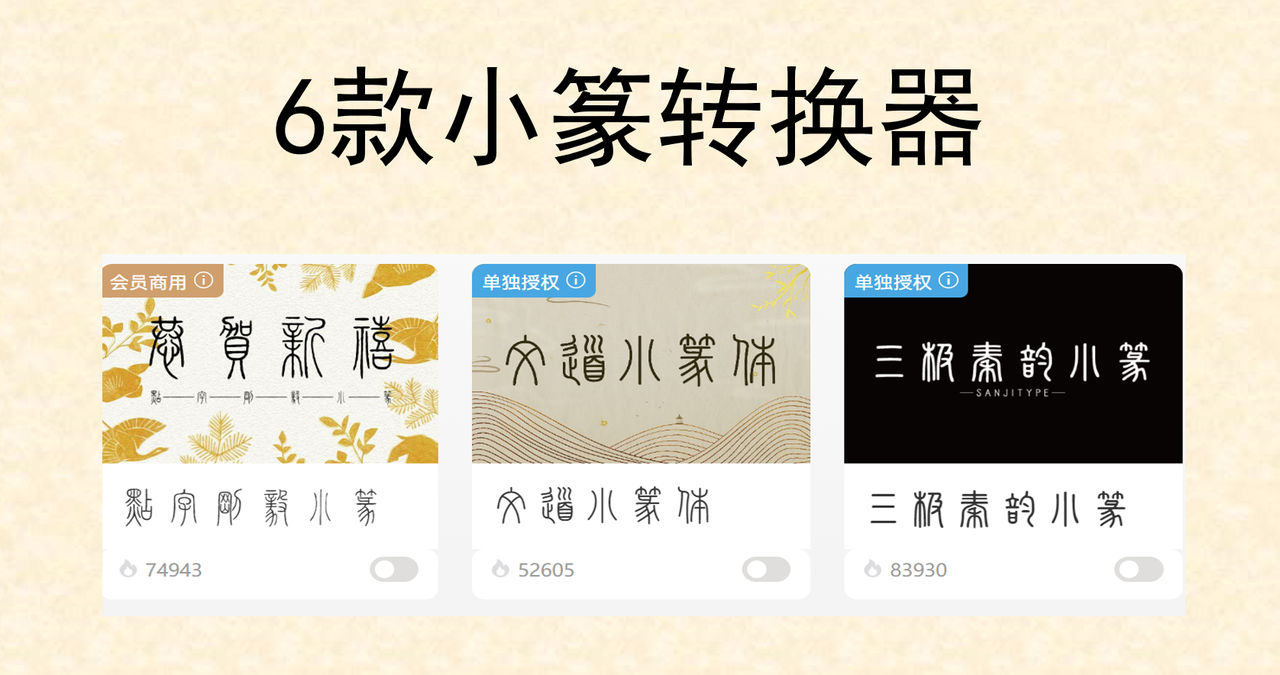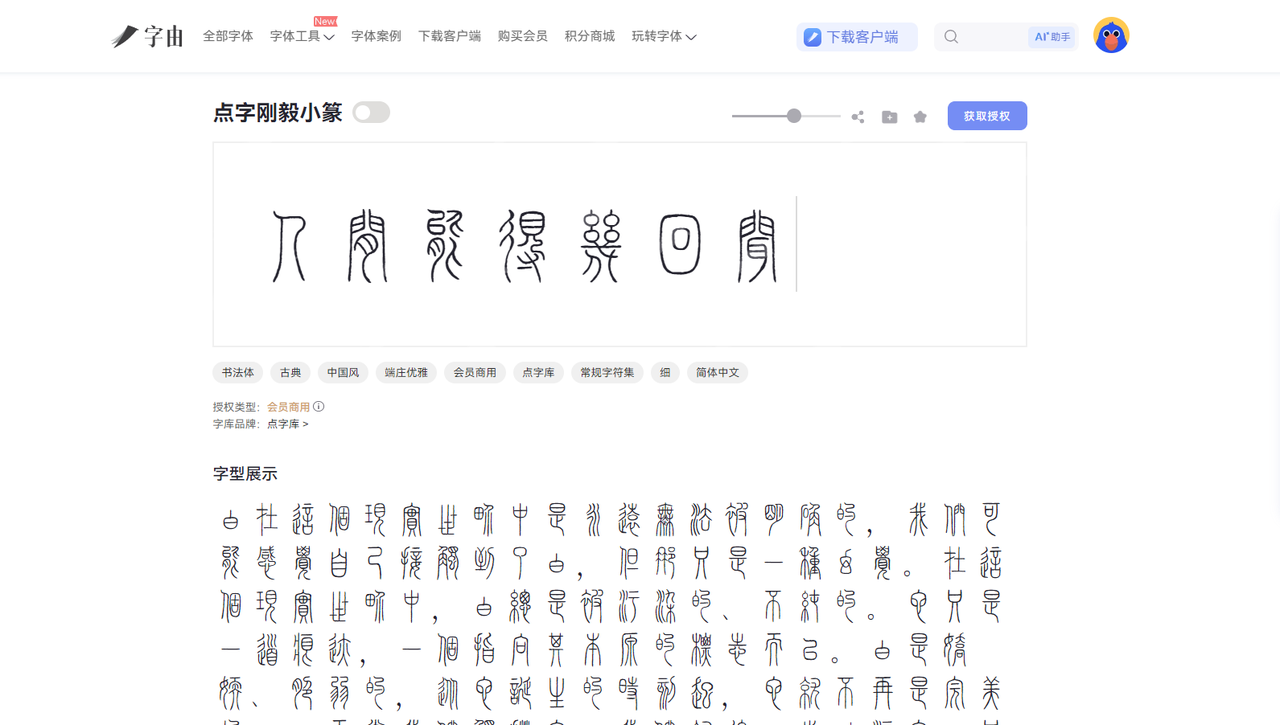
免费小篆转换器推荐,一键将汉字转换成标准小篆字体
小篆是秦代标准官方文字,线条婉转匀称,文化底蕴浓厚,是很多国风场景下经常会见到的一种字体类型。无论是品牌 logo、国风文创包装,还是篆刻印章,设计时加入小篆字体会瞬间提升作品的历史感和精致感。但是,我们日常使用的输入法是不能直接输出篆体字形的,想要把简体字快速转换为标准小篆挨踢,找到一款实用的小篆转换器至关重要。本文将给大家推荐 6 款优质且免费的小篆转换器,操作简单易上手、字体资源丰富,满足设计师、篆刻从业者、书法爱好者等各类人群的创作需求。
一、字由
字由是面向设计师用户提供字体应用,管理,授权服务,拥有 500+ 品质正版字体商用授权,并提供 AI 识字、字体特效等实用设计工具,是设计师必备的字体管理神器。在今天的所有转换器里面,字由是整体流畅度、篆体字资源、系统兼容性、实用性各方面都很完美的存在。
转换小篆的具体操作方法如下:
点击你心仪的小篆字体资源,在字体详情页面输入文案,它会自动生成对应风格的字体,你可以即时查看它的文字效果。
二、Stampdy
Stampdy 是专门用来设计制作篆刻印章的一个在线工具,可以轻松实现小篆字体转换,适配文创周边制作、姓名章、国风品牌设计等场景。用户打开该转换器之后可以直接选择“Seal Script 篆体模式”,输入名字,系统会自动转为小篆,而且还内置圆形、方形、椭圆形、瓦当四种传统印章版型,可自定义印章边框粗细、印泥深浅、文字布局等细节。你要是还觉得这个印章效果不够好,Stampdy 自带仿古做旧滤镜,一键即可生成斑驳拓印、老旧青铜印效果。如果你是专业从事篆刻印章行业的小伙伴,Stampdy 是最便捷且能达到预期效果的工具了。
三、 Chinese Calligraphy Generator
The Cantonese Cook 是一个书法字体生成器,内置多种小篆字体资源,主打生成毛笔质感的字体风格。用户无需注册,全程免费无广告,界面支持中英双语,对国内设计师超级友好。该工具支持自由调整毛笔笔触粗细、笔墨浓淡、纸张底色,还能添加水墨晕染、朱砂印等国风特效,无需搭配其他修图软件,在 The Cantonese Cook 就能一键生成小篆字体的国风画面。视觉效果上来说,普通小篆转换器只能输出单线条字体,而它转换出来的小篆有很强的手写感,比较还原真实书写的效果,再配上古风背景,艺术氛围感极强。除此之外,它还支持批量导出多版本效果图,免费用户单次可保存 5 张不同底色、笔触样式的小篆图片,图片质量高清,满足印刷需求。
四、Akuziti
Akuziti 是海外独立运营的多语言艺术字体转换器,内置独立小篆转换分区,支持一键生成空心篆体、渐变金属质感篆体等艺术字,可以直接用于国潮电商海报、国风短视频封面等场景。与其他小篆转换器相比,Akuziti 提供了大量绚丽的视觉特效,比如渐变、浮雕、发光、磨砂、液态金属等等,用户可以在转换完成后自行添加这些效果。对于需要大批量转换篆体字的用户来说,Akuziti 一次性可以转换十组不同配色小篆素材,自动压缩打包,大幅提升设计师素材产出效率。
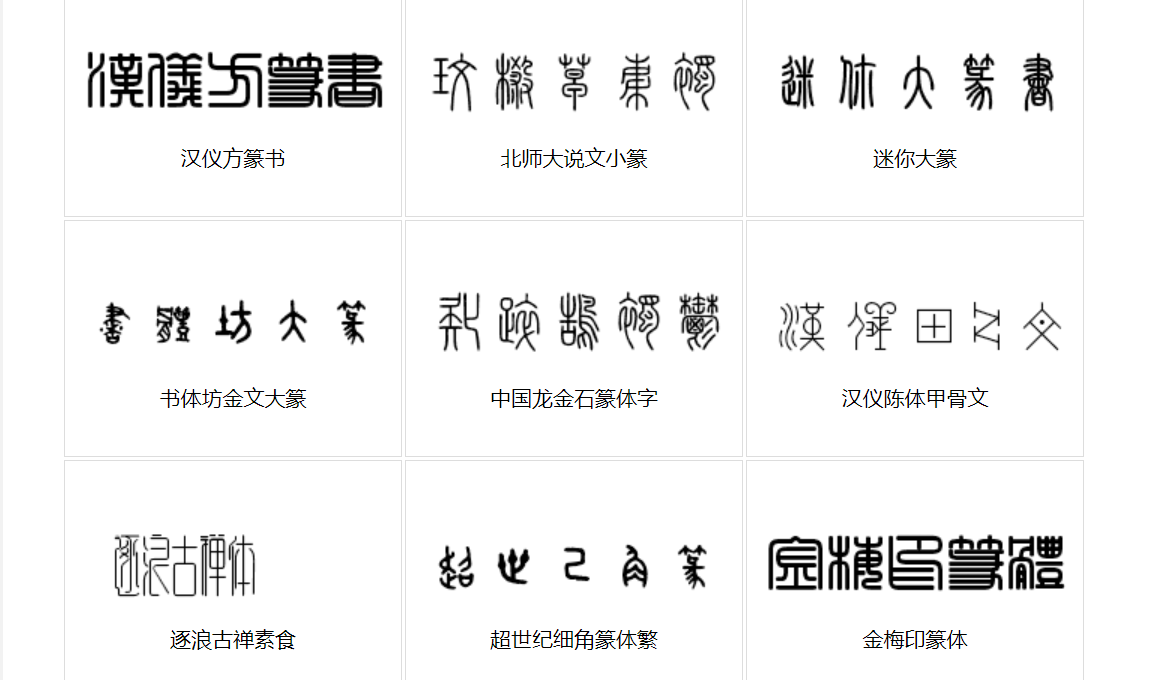
五、Calligraphy Tools Stone & Water Studio
Calligraphy Tools Stone & Water Studio 是一个主打复古拓片质感的篆体转换工具,主要免息那个海外汉语爱好者、手工篆刻创作者,转换字体的效果堪称是同类工具天花板级别。在这里输入文字,系统会自动生成自带斑驳、磨损、裂纹的拓片滤镜,效果逼真且自然。当然,该工具也给了用户充分的操作自由度,你可以自行调整拓印深浅、复古效果、裂纹程度、纸张做旧程度等等,还能调整文字竖排模式,这一功能非常适配书法、国风画作、博物馆科普展物料这类场景。最关键的一点是,Calligraphy Tools Stone & Water Studio 转换小篆没有任何的字数限制,你甚至可以直接输入长篇的古文,它都能一次性完成转换。
六、Chinese Seal Script Generator
与上面的几款小篆转换器都不一样,Chinese Seal Script Generator 是极简轻量化的工具,特点就是占用内存低、转换速度快,适配手机、电脑多设备使用。由于该工具的网页占用体积极小,除了小篆转换没有多余的功能,即使是网络环境较差也能流畅使用,对于经常外出的创作者们非常友好!如果你只是需要一种小篆字体,不要求绚丽的外表,追求极简设计,Chinese Seal Script Generator 是个很好的选择。
以上就是为大家精心挑选的 6 款小篆字体转换器,功能优势各不相同,大家根据自己近期的需求来选择哦。字由不仅字体资源丰富、字体版权清晰,而且客户端一键应用字体,不用下载字体文件;Stampdy 擅长制作印章;Chinese Calligraphy Generator 可以生成毛笔质感的字体风格;Akuziti 拥有大量视觉特效;喜欢复古质感小篆的选择 Calligraphy Tools Stone & Water Studio;Chinese Seal Script Generator 则更适合经常外出的创作者,手机端也能使用。这些工具的基础转换功能都是免费使用的,能够满足绝大多数国风相关的设计场景,大家自己尝试一下吧!